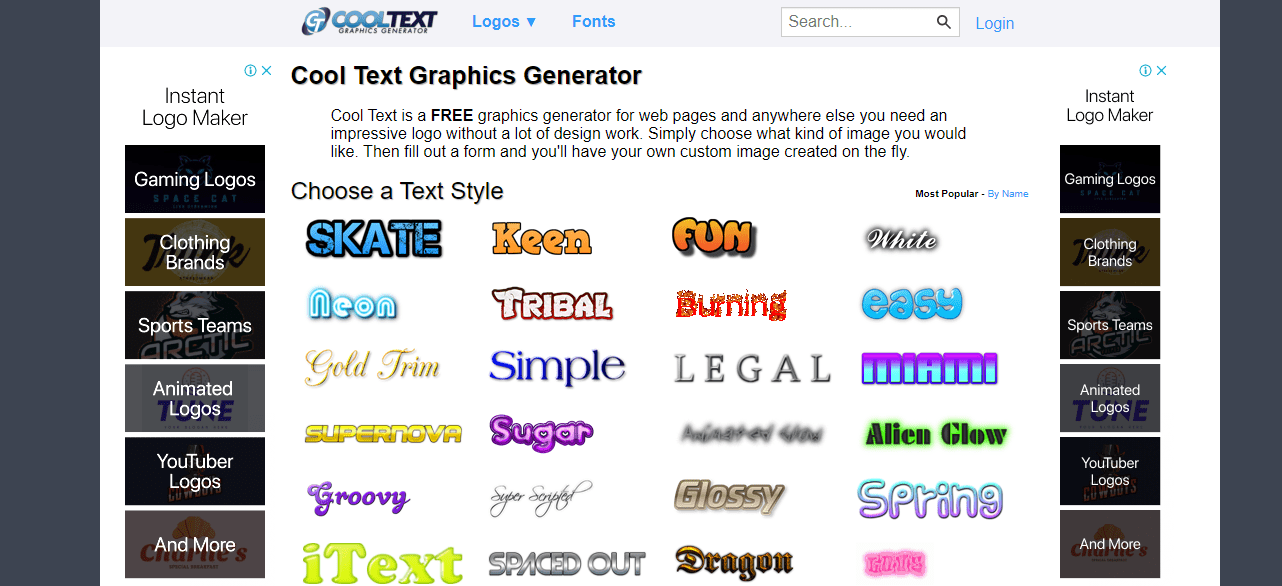
Font Chữ Nghệ Thuật Cực Đẹp Miễn Phí Dowload 2021 - In Nhãn Mác
Các bạn đang tìm kiếm bộ font chữ nghệ thuật cực đẹp để thiết kế banner, slogan, poster… hay đơn giản các bạn muốn in chữ lên áo, hoặc sử dụng cho mục đích học tập, làm việc, giải trí của riêng bạn. Vậy các bạn hãy tham khảo bài viết dưới đây, bài viết dưới đây In Nhãn Mác sẽ chia sẻ đến các bạn bộ font chữ nghệ thuật cực đẹp đã được Việt hóa, mời các bạn theo dõi.
Nếu bạn vẫn không rõ font chữ nghệ thuật là gì thì bọn tôi có thể chia sẻ nhỏ. Đây là những Font chữ bạn thường xem trên những mặt hàng thời trang, quà lưu niệm. Hay áp phích các kế hoạch nghệ thuật, font chữ nghệ thuật được rất đông nhà xây dựng chuộng. Sử dụng cho các kết quả của bản thân. Vậy font chữ nghệ thuật là gì ? Làm sao để dùng font chữ nghệ thuật, hãy cùng khám phá dưới đây nhé.
Cùng tìm hiểu font chữ nghệ thuật là gì?
Font chữ nghệ thuật là Font chữ viết bình thường. Tuy nhiên các đường nét được cách điệu mềm mỏng cong lượn để đem đến tính khêu gợi nét thẩm mỹ trong chữ viết. Theo nhiều nhà xây dựng gốc tích của chữ nghệ thuật được xem là và chào đời, nổi tiếng ở Trung Quốc đại lục. Với chữ viết thực sự là chữ Hán tượng hình. Được viết theo những phương pháp phức tạp hơn tạo nên cái đẹp như rồng bay phượng múa. Giúp trình bày nghệ thuật chơi chữ tượng hình của người Trung Quốc đại lục.
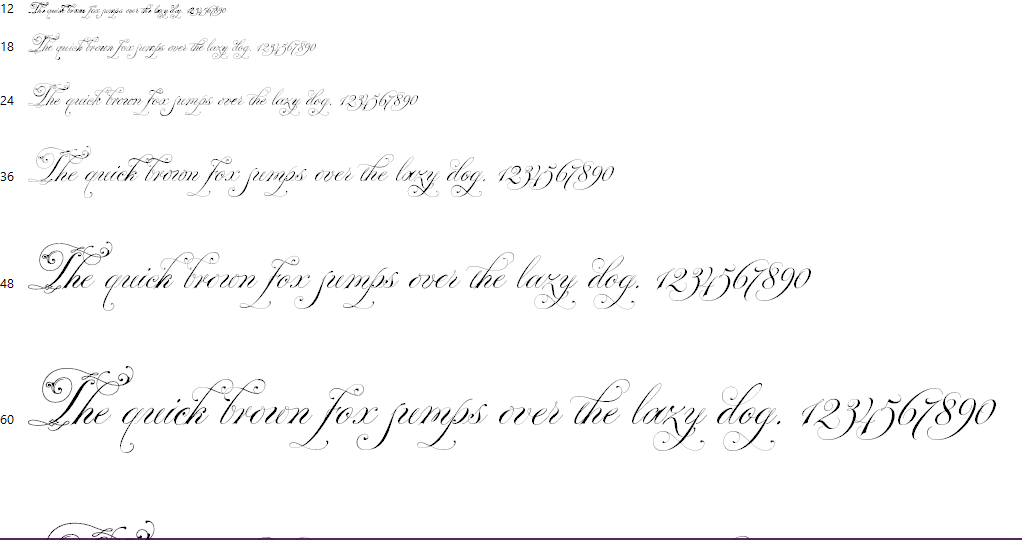
Bây giờ với sự phổ quát của công nghệ thông tin và sự hội nhập kết hợp phong tục tập quán. Font chữ nghệ thuật được sử dụng rộng rãi trên toàn cầu. Nổi bật với vài người làm công việc xây dựng thì Font chữ nghệ thuật càng lúc càng trở thành quen thân.
Muốn dùng font chữ nghệ thuật thì phải làm như thế nào ?
Tùy từng tình huống, mục tiêu, Font chữ nghệ thuật được ứng dụng để nâng cao việc đọc – Text typography hoặc để hiển thị – Display typography hoặc làm việc. Hữu hiệu của font nghệ thuật sẽ được nâng tầm qua cảm nghĩ của người làm công việc xây dựng.
Điều đó tạo ra sự khác lạ lớn đến cách đọc và cảm nghĩ về lời nhắn được gởi gắm. Qua xây dựng đó. Và đương nhiên, hữu hiệu typography có được hầu hết. Dựa vào các điểm về phối hợp font, kích cỡ, cự li và sắc thái …
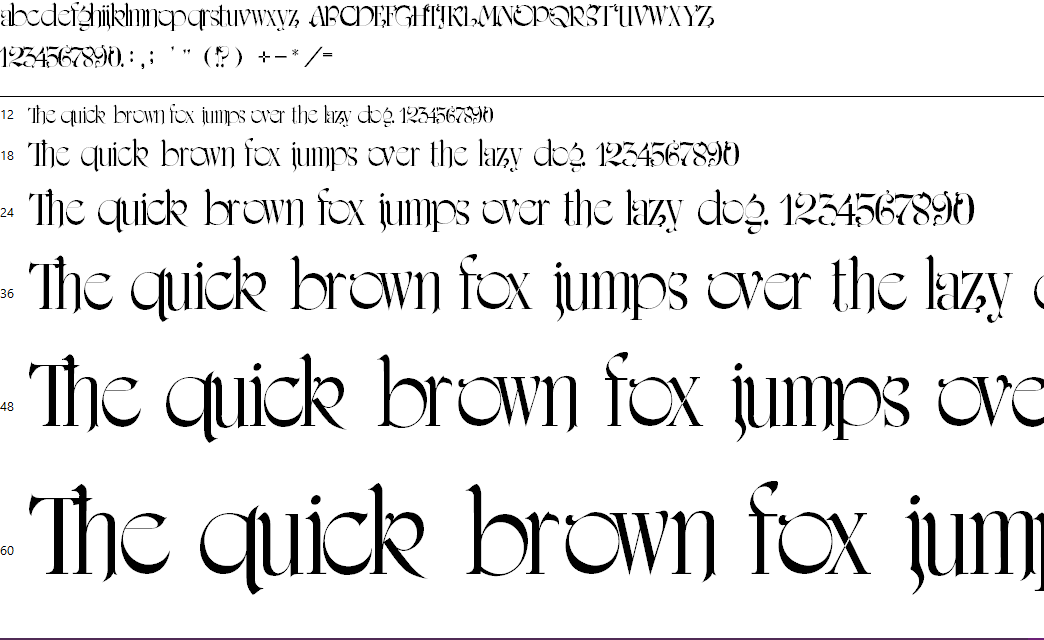
Điều đó sẽ hơi phiền nhiễu giả định bạn thiếu hẳn chút vốn hiểu biết nào về máy vi tính. Làm cho bạn giải tỏa những phiền nhiễu này. Các nhà phá cách đã phân phối những dụng cụ tạo Font chữ nghệ thuật lên mạng. Hỗ trợ việc tạo chữ nghệ thuật đã trở thành đơn giản và thuận lợi hơn cực kỳ nhiều.
Giả định những người có yêu cầu tạo chữ nghệ thuật. Mà không thèm khát sử dụng các dụng cụ lâu nay như những ứng dụng offline. Thì những người khả dụng những dụng cụ tạo chữ nghệ thuật trực tuyến. Sau đây là chỉ dẫn cách tạo font nghệ thuật lên mạng phổ biến.
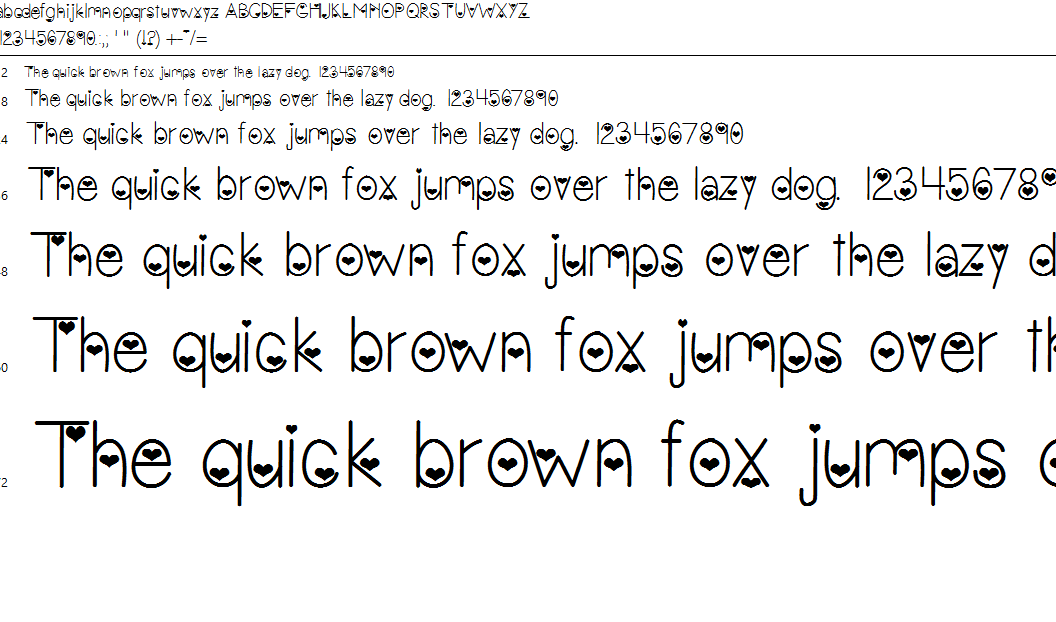
Tạo font nghệ thuật trực tuyến bằng dụng cụ Textfx
Để tạo font nghệ thuật lên mạng bằng dụng cụ Textfx.
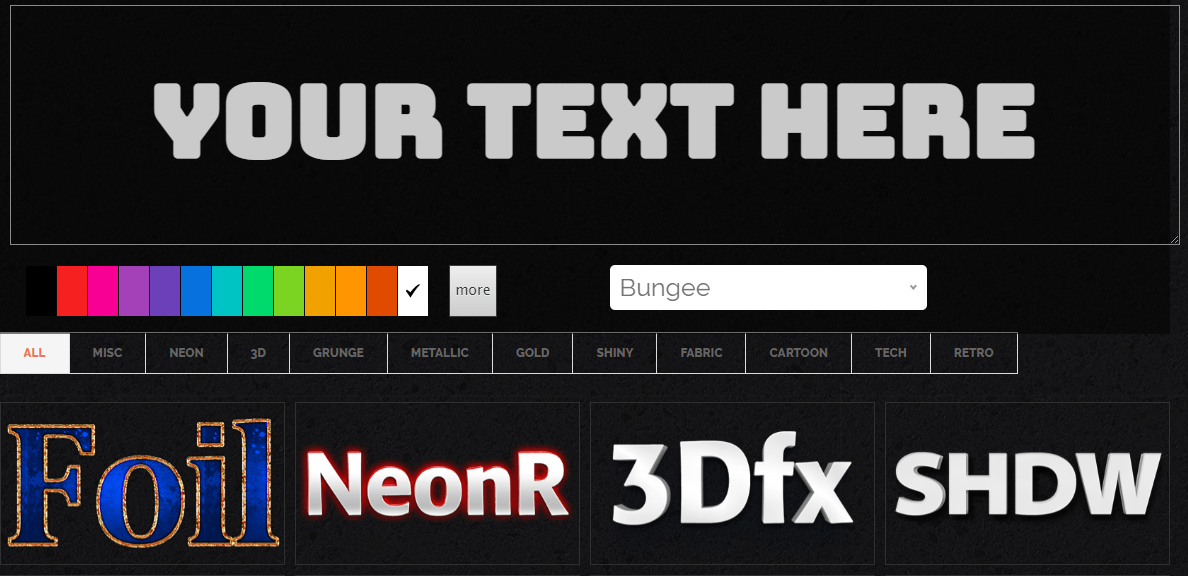
Textfx là 1 dụng cụ phá cách chữ nghệ thuật online đơn giản. Cách hoạt động sử dụng thuận tiện. Người dùng khả dụng các mẫu chữ nghệ thuật hiện có trên ứng dụng. để tự tạo nên các mẫu chữ cho chính mình, hợp với yêu cầu của mình.
Textfx có được các mẫu hiệu ứng y như trên các tờ áp phích phim nức danh. Nên nếu bạn thích trường phái này thì đây sẽ trở thành dụng cụ tạo font nghệ thuật ruột cho bạn.
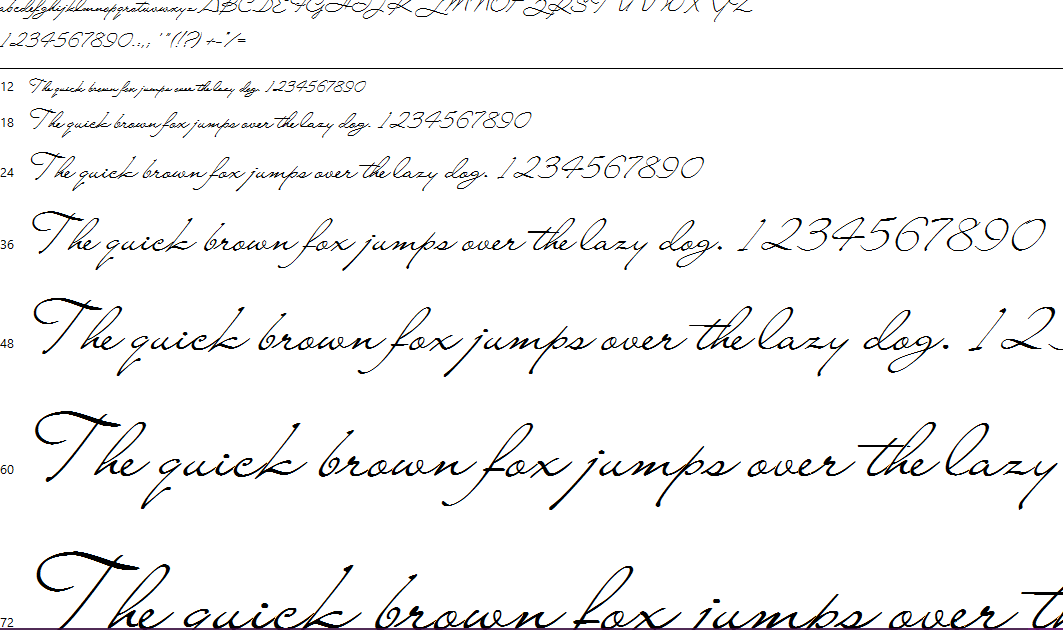
Tạo font nghệ thuật trực tuyến bằng dụng cụ Flamingtext
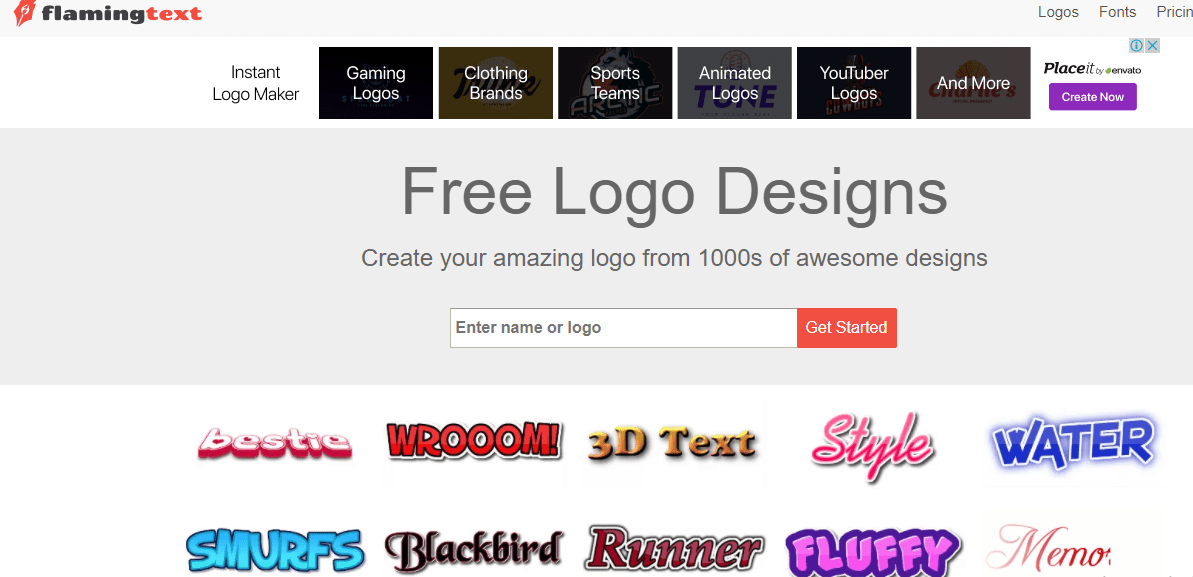
Dụng cụ Flamingtext có bản quyền 1 kết nối thông tin khách hàng đơn giản. Dễ sử dụng đi cùng với nhiều mẫu chữ phong phú hỗ trợ khách hàng có khả năng tạo. Các hiệu ứng chữ nghệ thuật cực kỳ dễ dàng.
Tạo font nghệ thuật lên mạng bằng dụng cụ Textpro
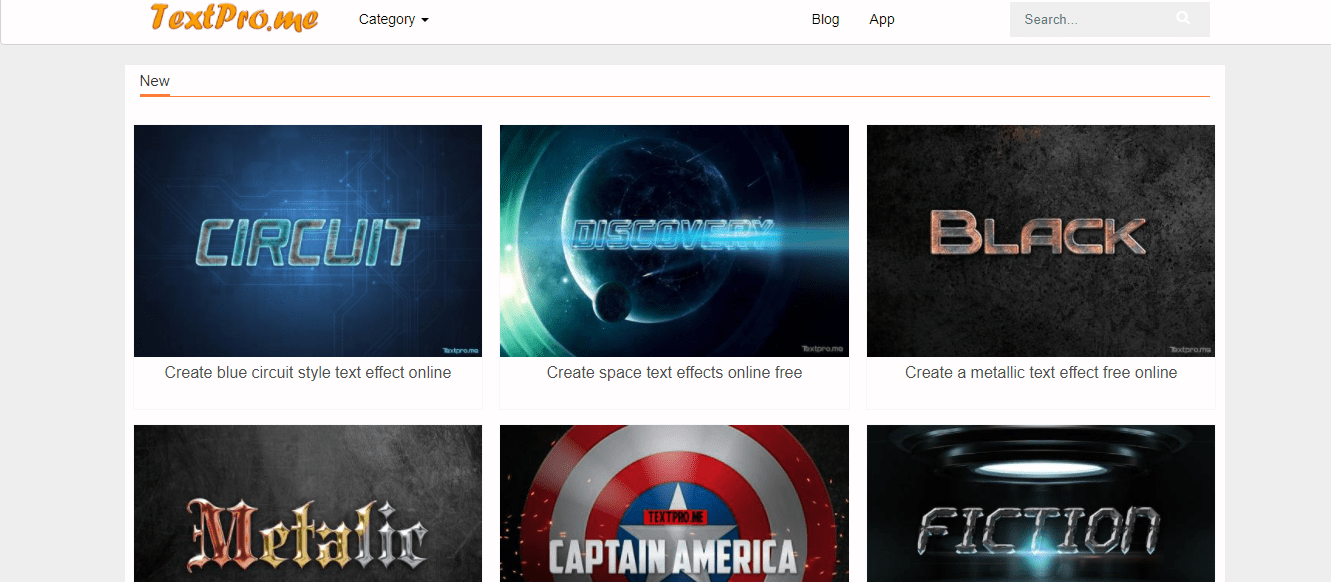
Textpro là một trong những dụng cụ tạo chữ nghệ thuật trực tuyến không lấy tiền. Có các mẫu chữ đẹp và và phong phú nhất trên thị trường thời nay.
Các Font chữ nghệ thuật của textpro được phân phân thành nhiều đề tài không giống nhau như :
Đề tài khoa học
Thiên nhiên
Thực phẩm
Viễn tưởng, …
Bổ sung cho khách hàng quá nhiều định dạng không giống nhau để hỗ trợ khách hàng tự do sáng tạo ra sản phẩm của riêng bản thân mình.